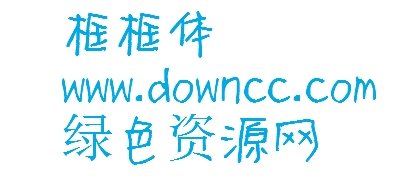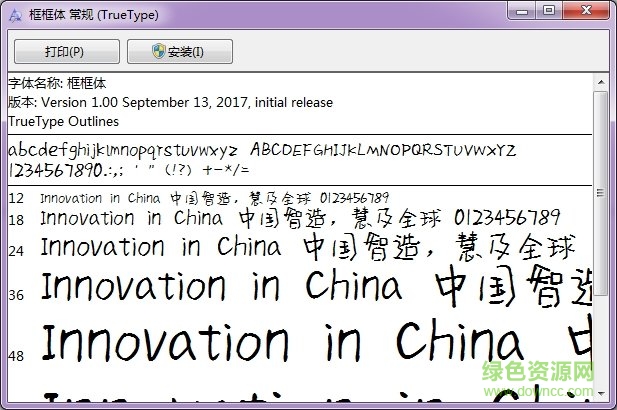
框框體ttf是一款簡明隨意的手寫字體,文字不拘泥中規(guī)中矩的楷體和宋體,給人清晰直觀的板書呈現(xiàn),是一款效果極佳的pop字體,綠色資源網(wǎng)今日推薦!
框框體是一款優(yōu)美個性的字體,能夠讓你的平面設(shè)計作品更加令人印象深刻,可以廣泛應(yīng)用于平面設(shè)計、影視海報、卡通畫集等方面,非常實用!